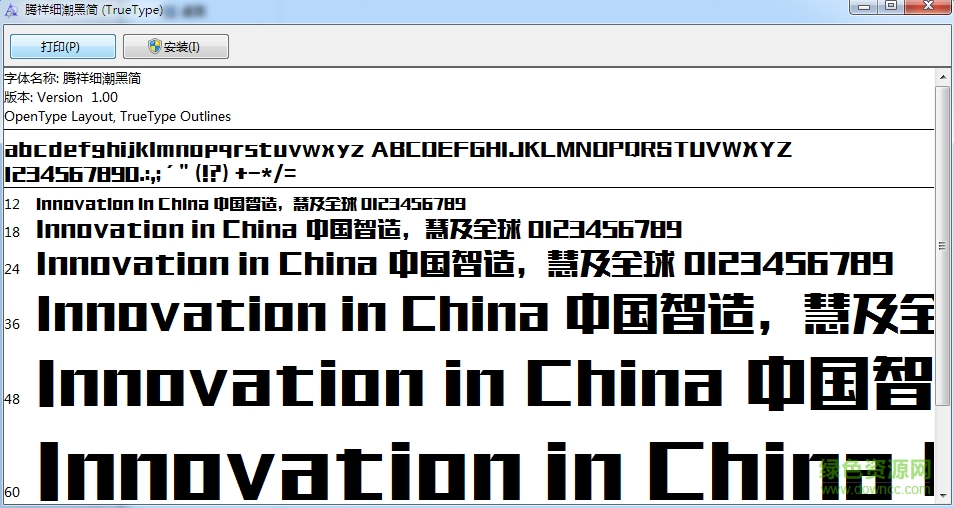
tensentype chaoheij是騰祥字庫(kù)中一款非常有特色的黑體字體,這款字體的字形顯得非常的方,并且黑的非常的突出,有需要的朋友歡迎下載使用!
tensentype chaohei就是我們常見(jiàn)的騰祥細(xì)潮黑簡(jiǎn)體字體,是一款筆畫(huà)細(xì)膩的黑體字體,整個(gè)字體看上去就會(huì)非常的顯眼,非常的有特色,適合用到各種創(chuàng)作中!